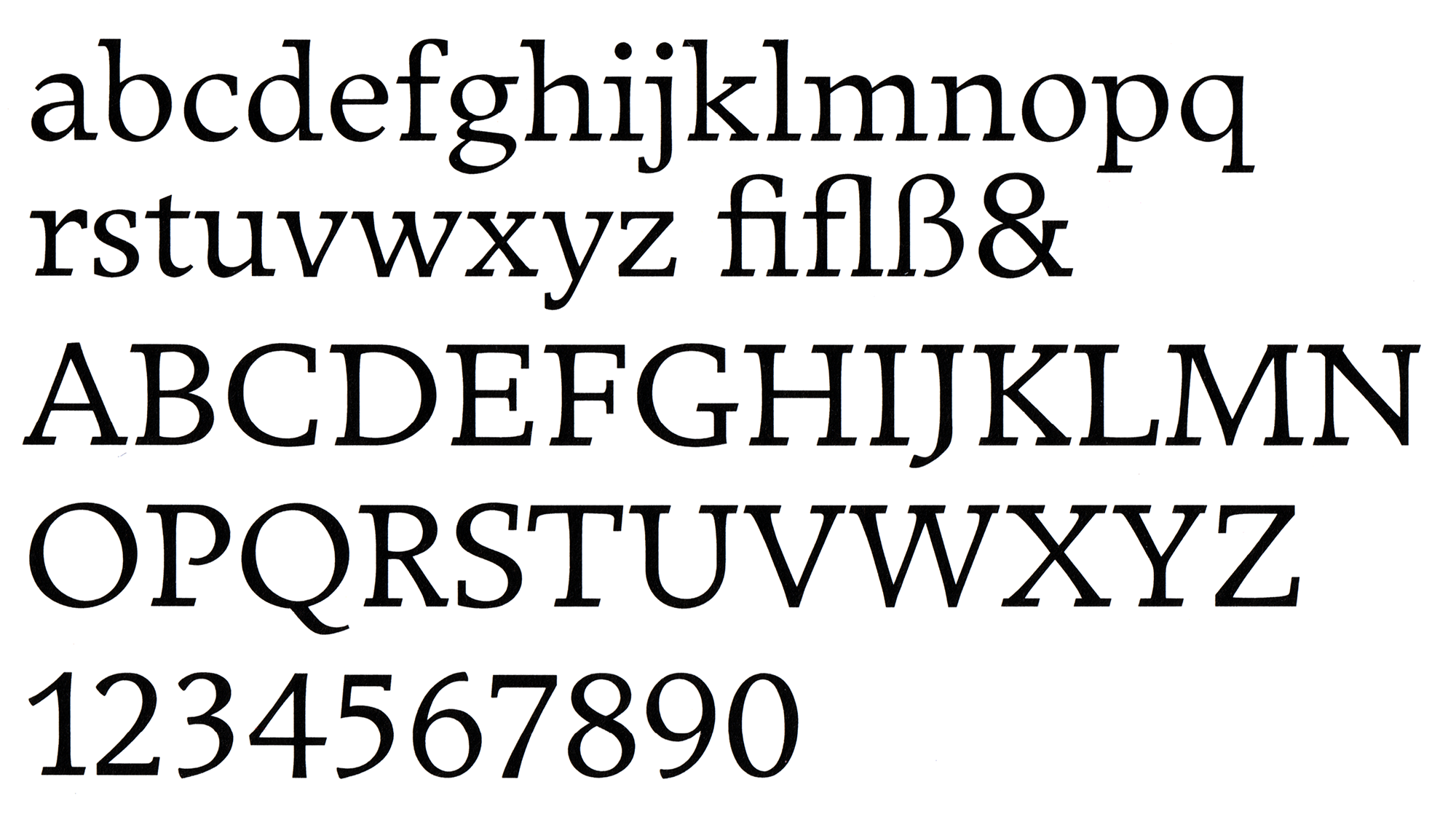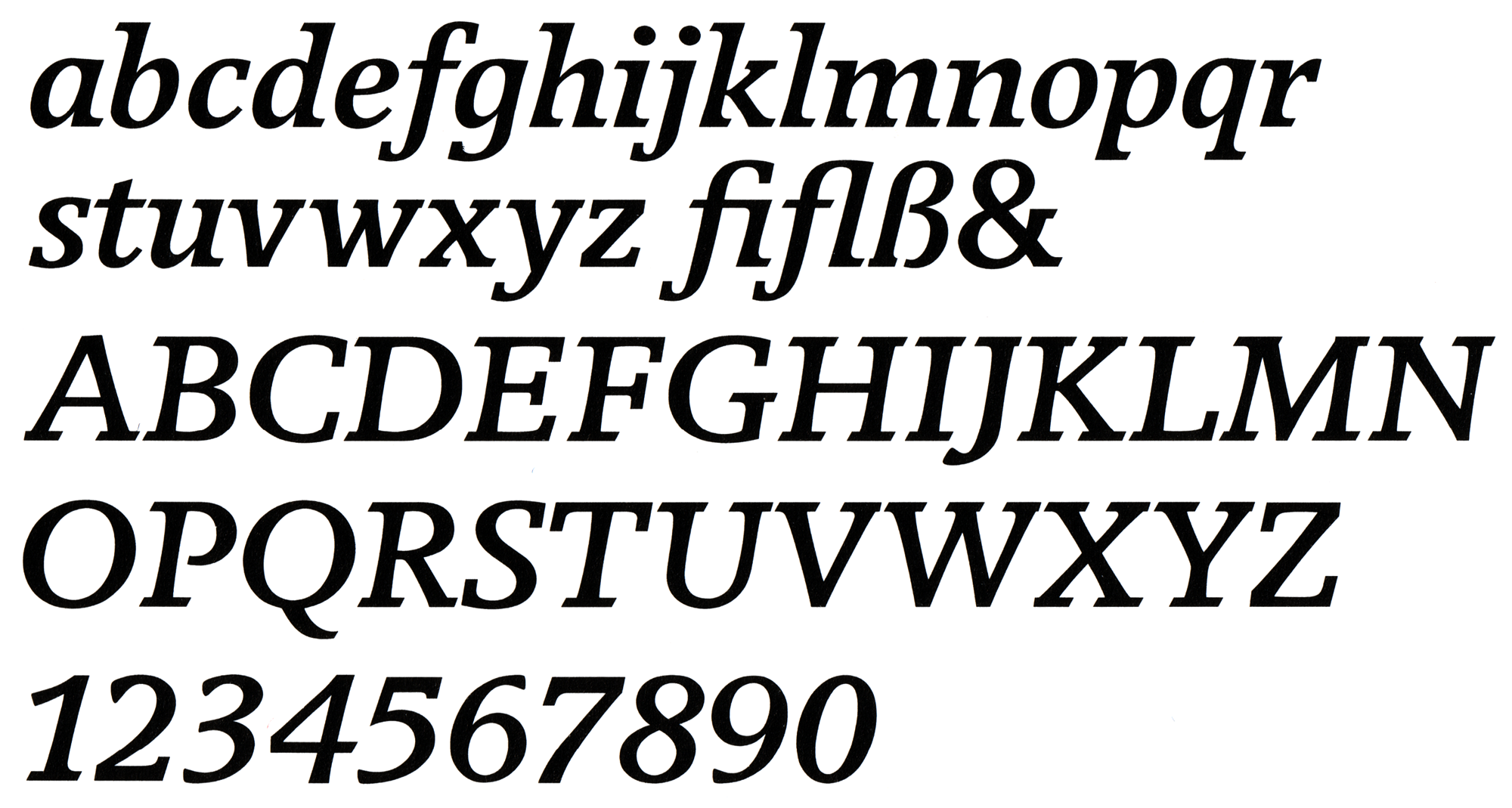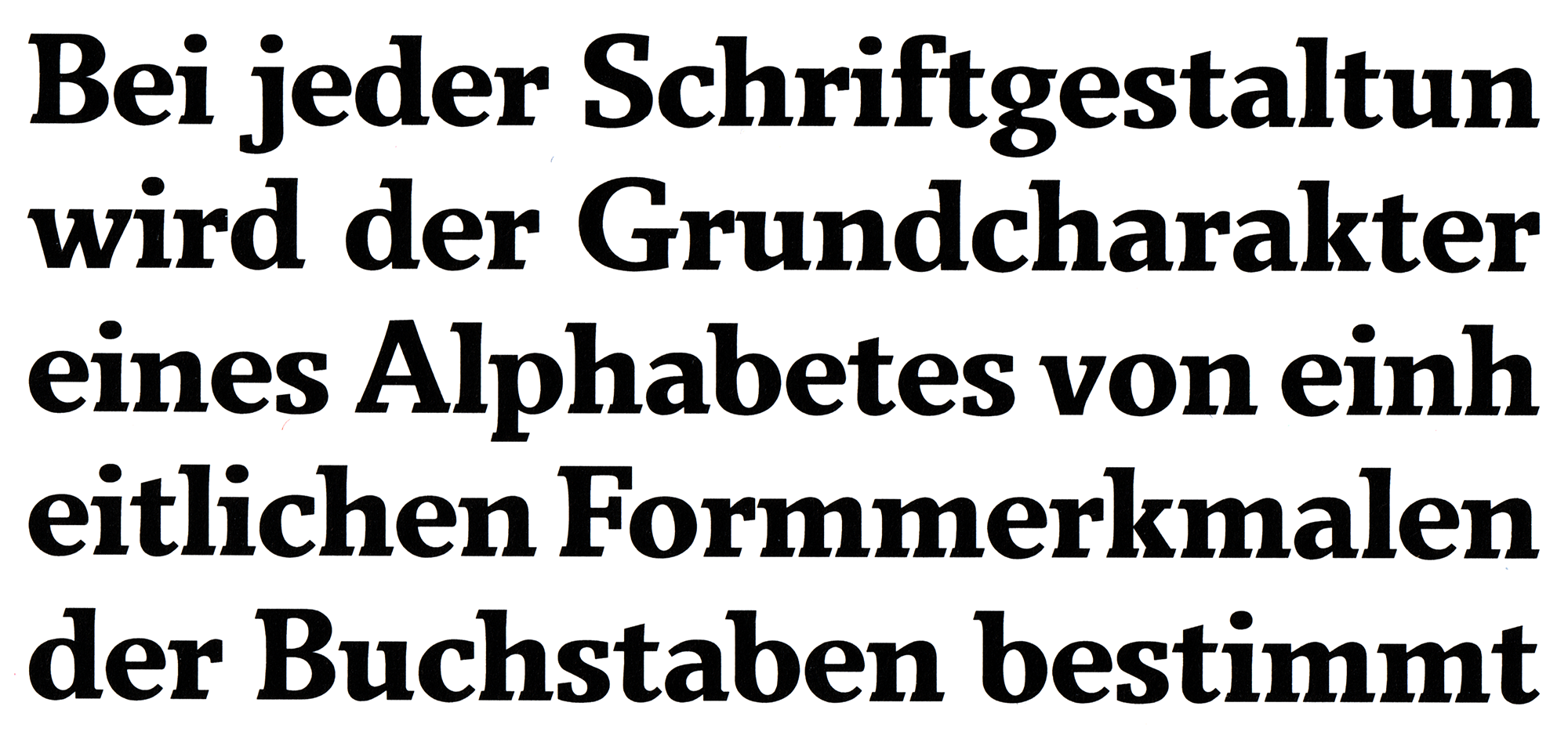
- 1981
- Antiqua humanistisch
Die Breughel ist eine Antiqua-Schrift von Adrian Frutiger. Der Entwurf wurde Ende der 1970er-Jahre begonnen und die Schrift erschien Anfang der 1980er-Jahre. Die Gestaltung ist speziell auf die rasterbasierten Kathodenstrahl-Fotosatzsysteme der Zeit ausgelegt. Frutiger fand etwa die Darstellung seiner Méridien in diesen Systemen »schockierend« und entwickelte mit der Breughel Antiquaformen, die die entsprechende Digitalisierung und Belichtung besser überstanden.